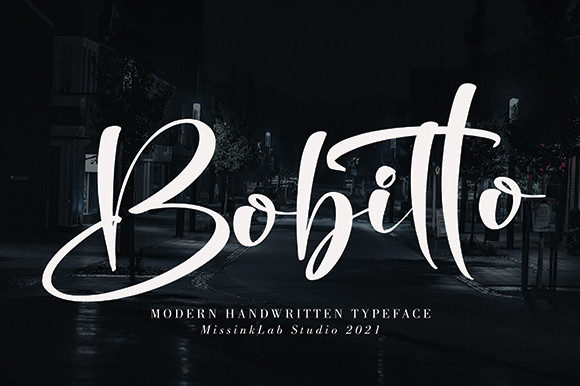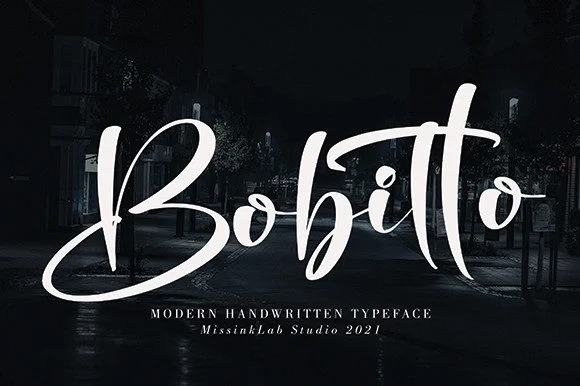
Название: Bobitto Font (2021)
Bobitto - элегантный и изящный рукописный шрифт с милыми и нежными мазками.
Этот оригинальный шрифт подойдет для широкого круга рукодельных идей, от бланков и заголовков до канцелярских принадлежностей.